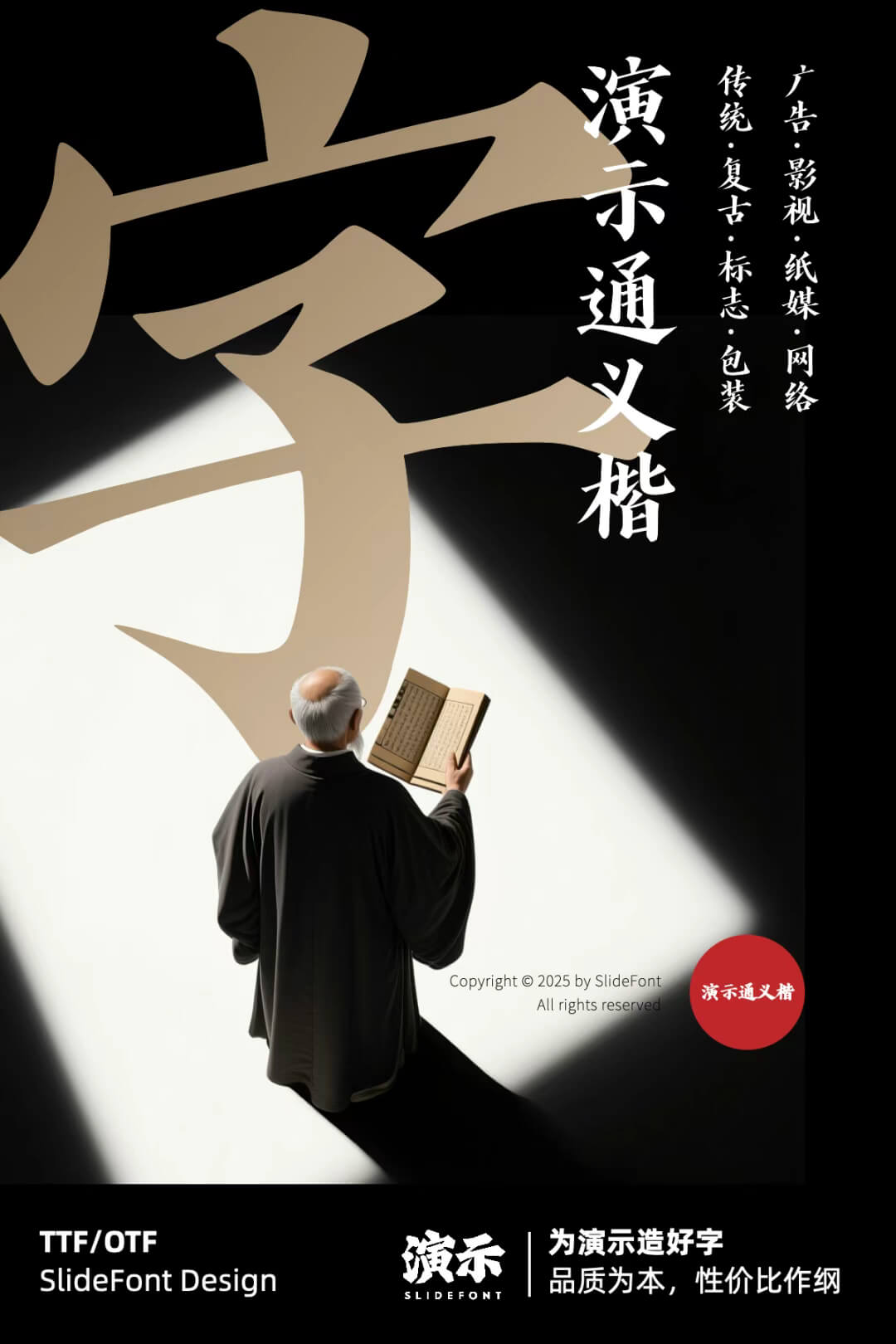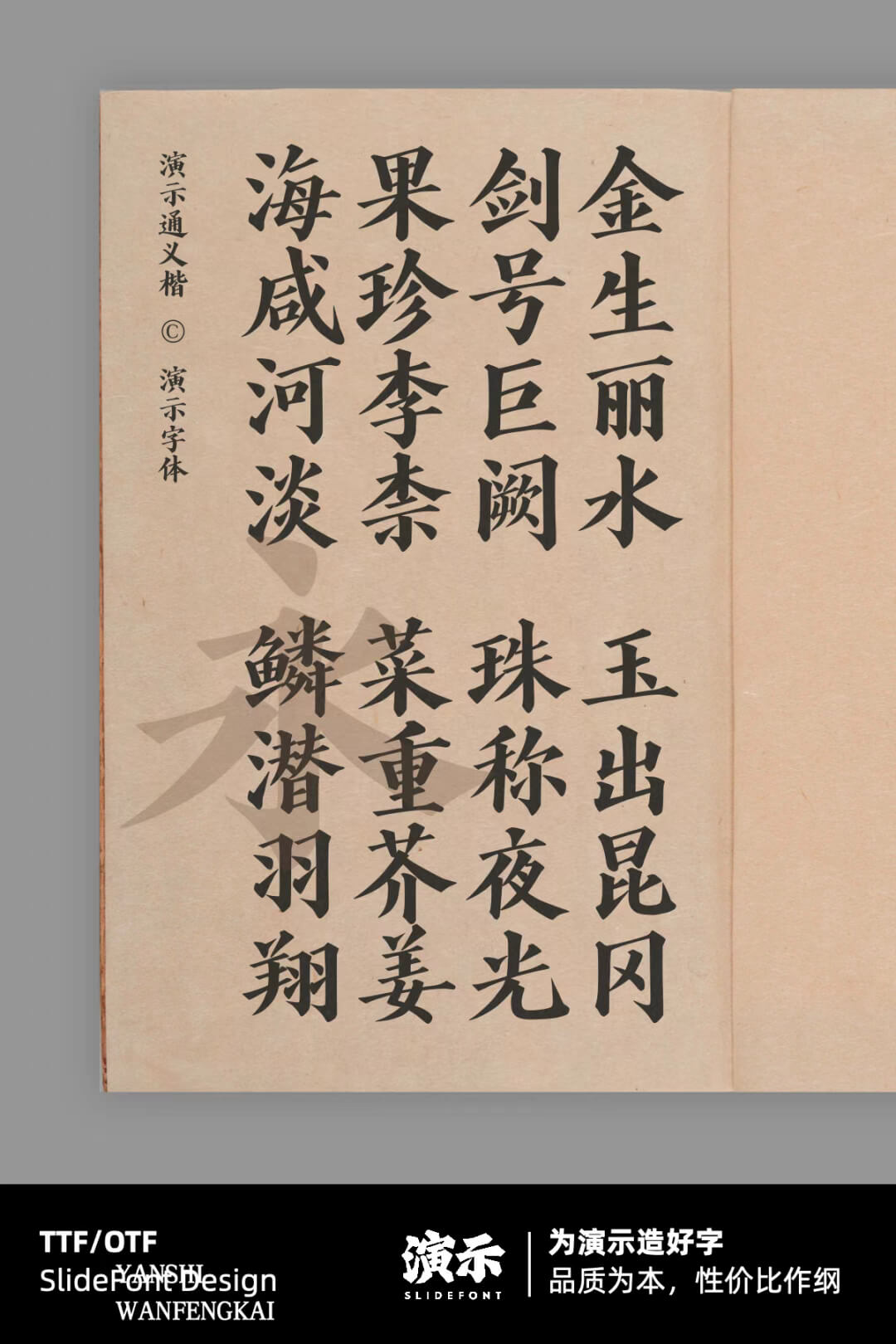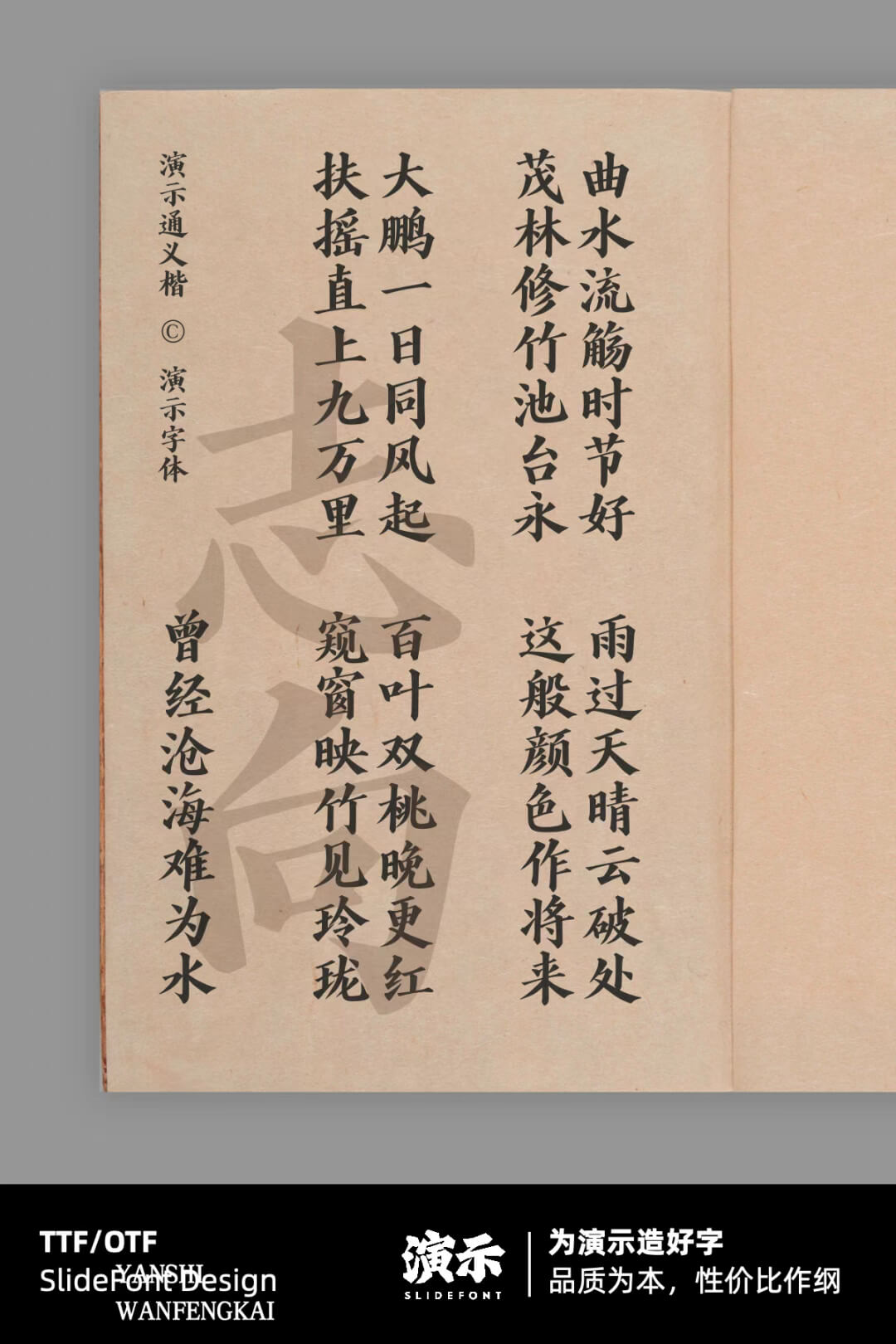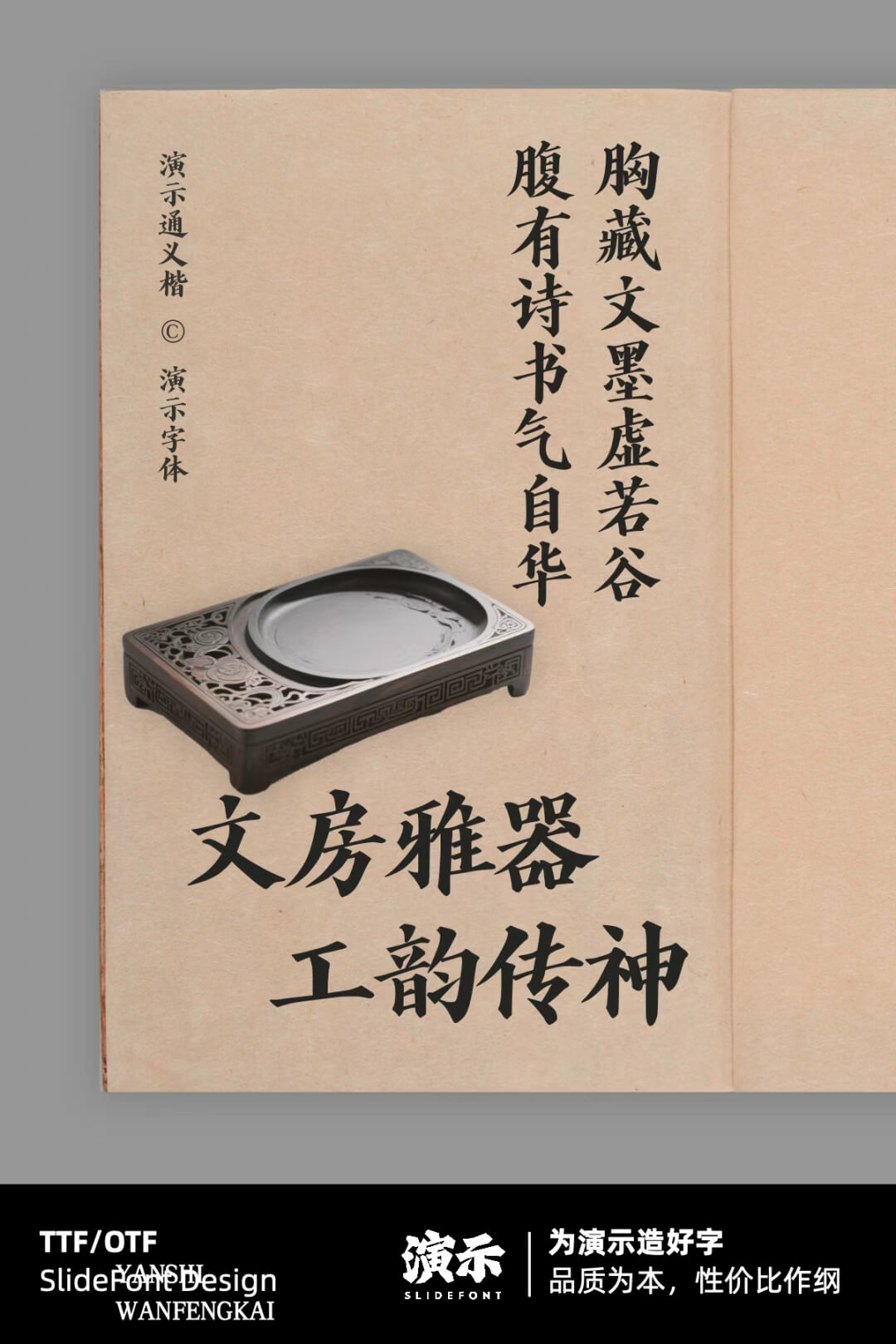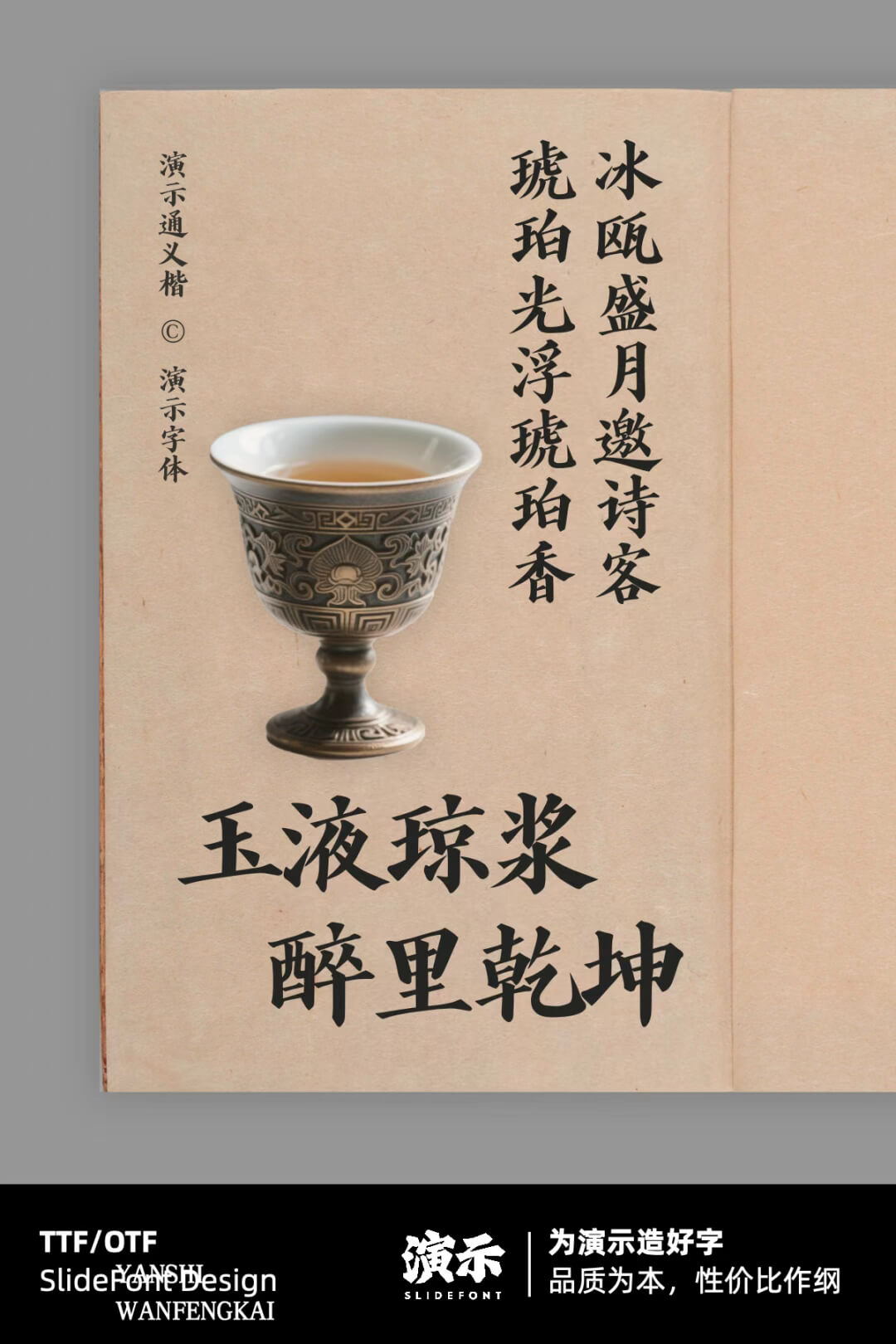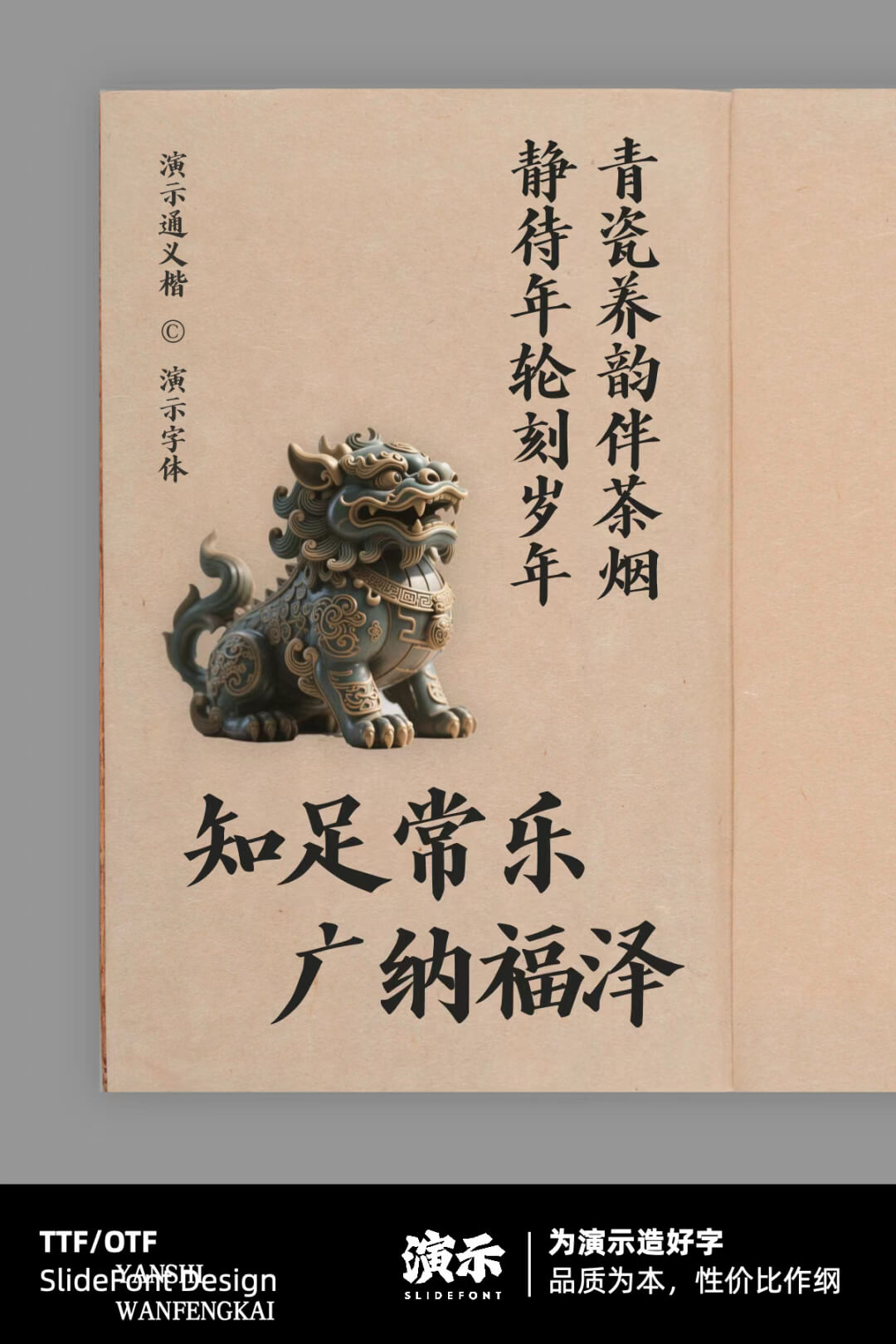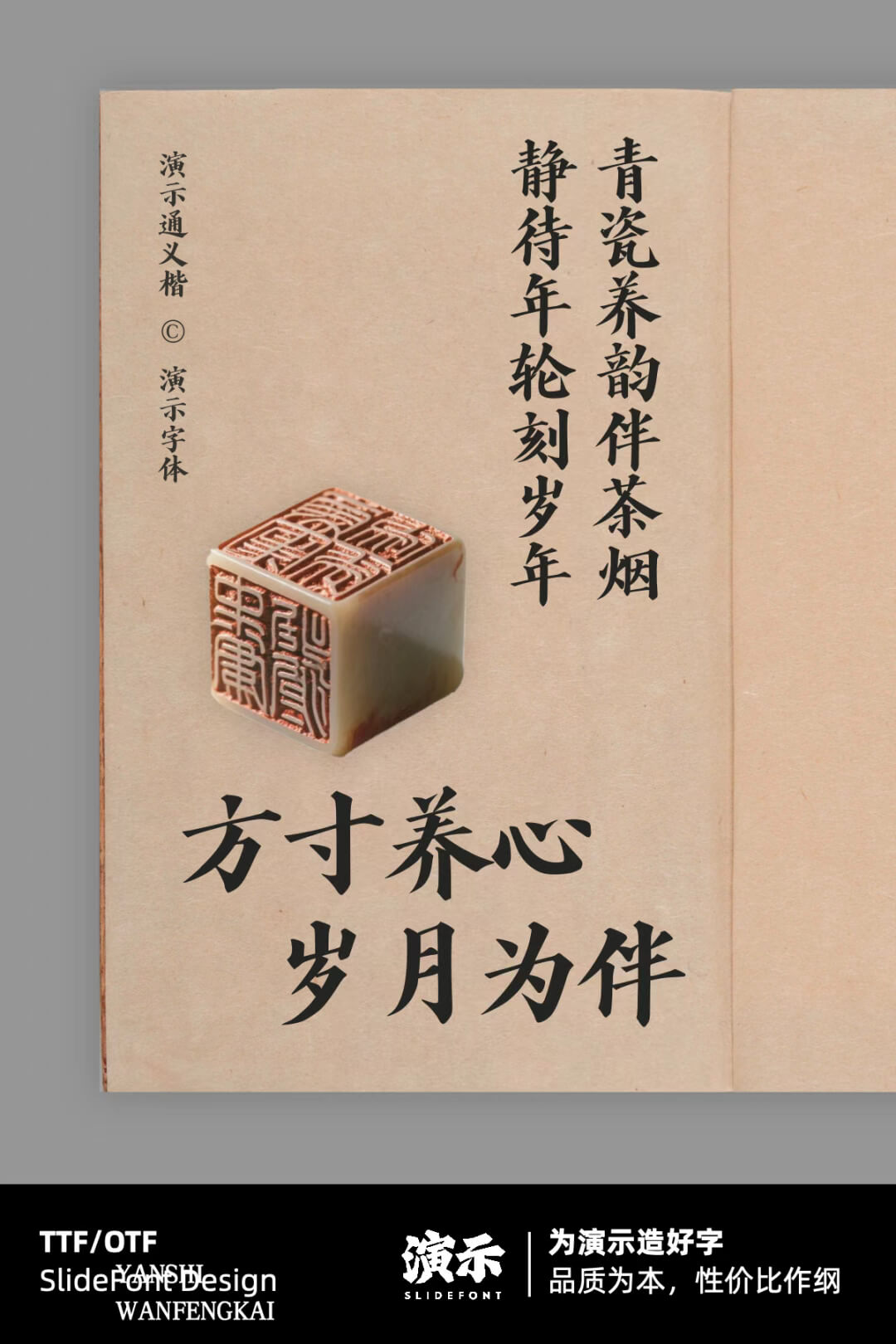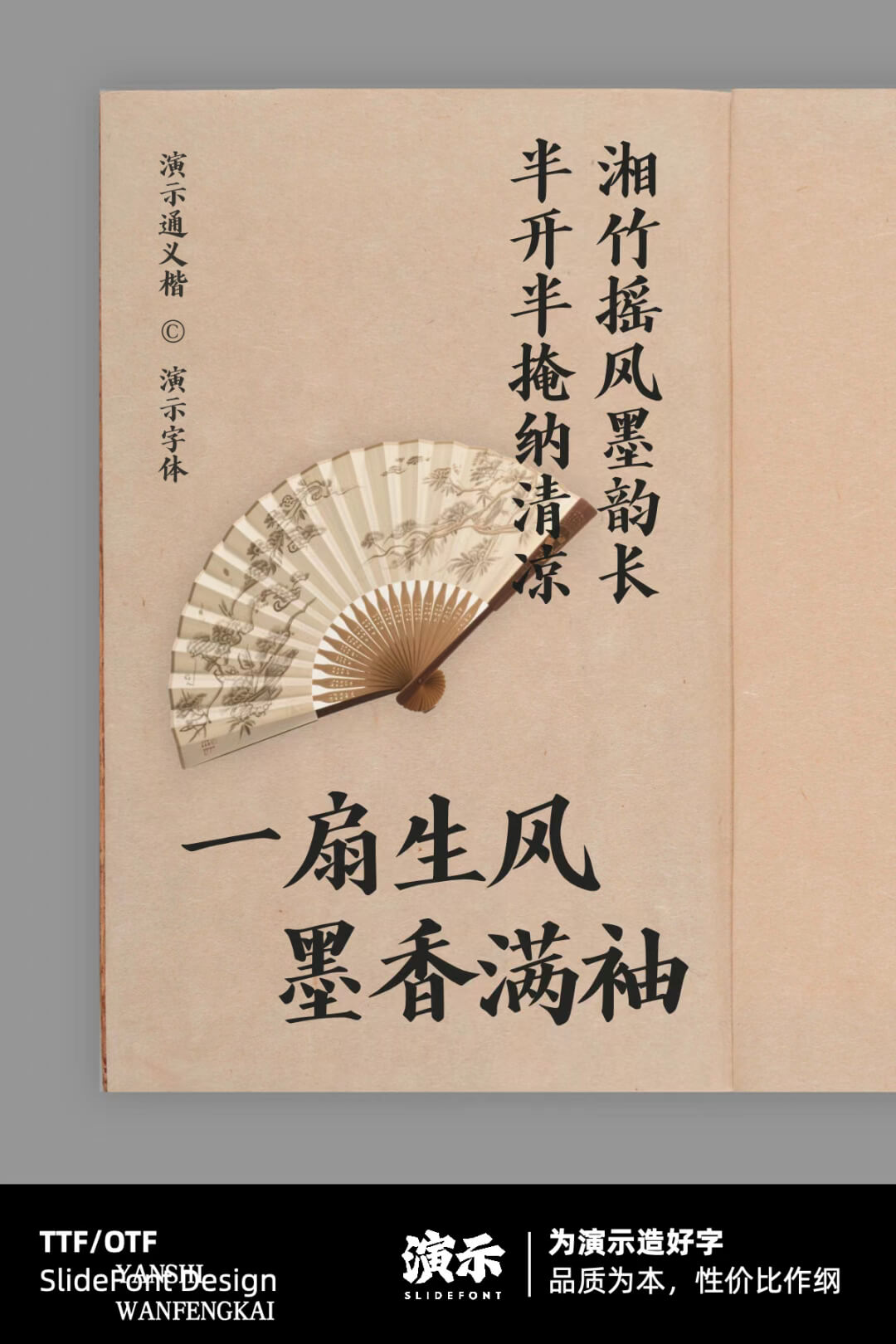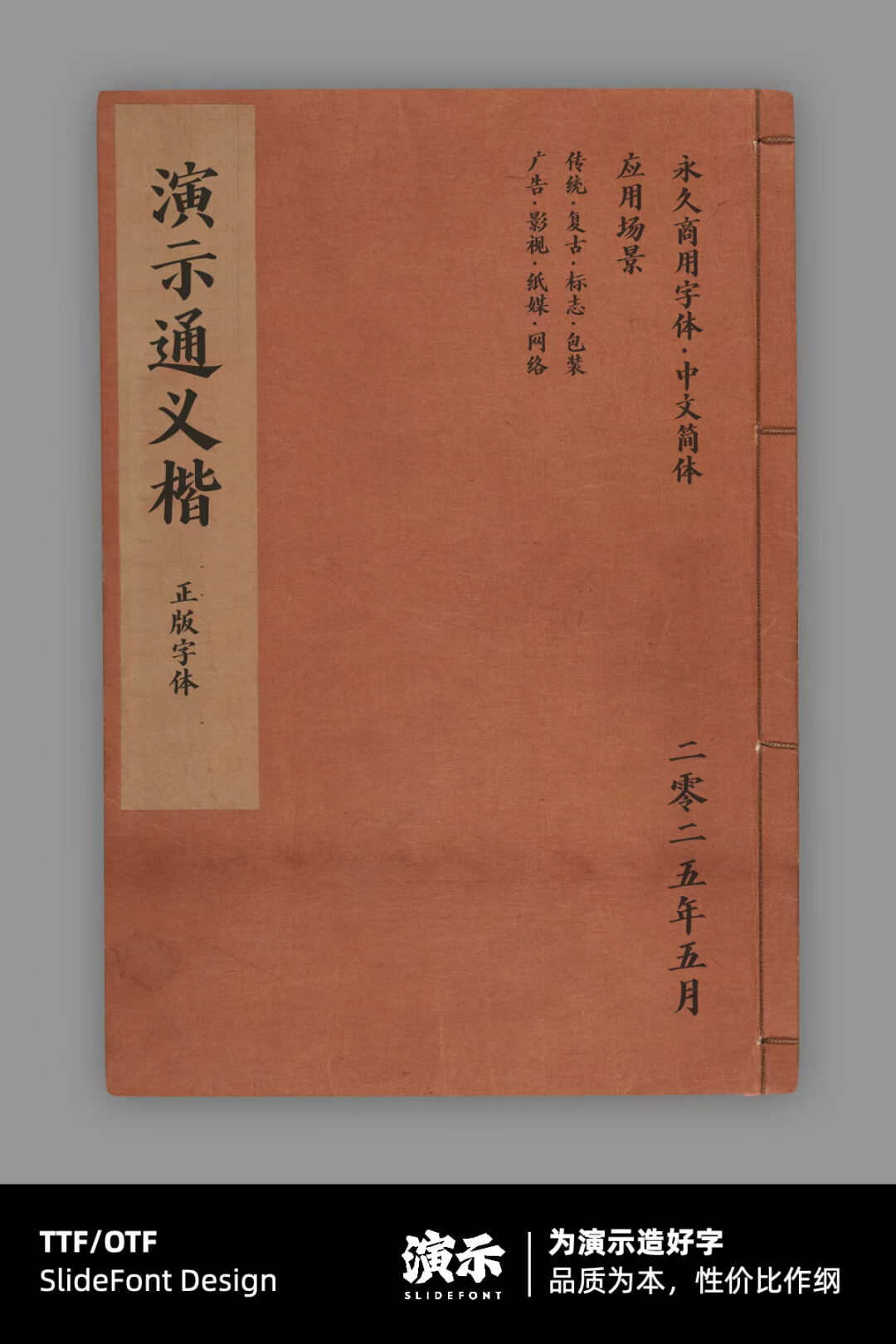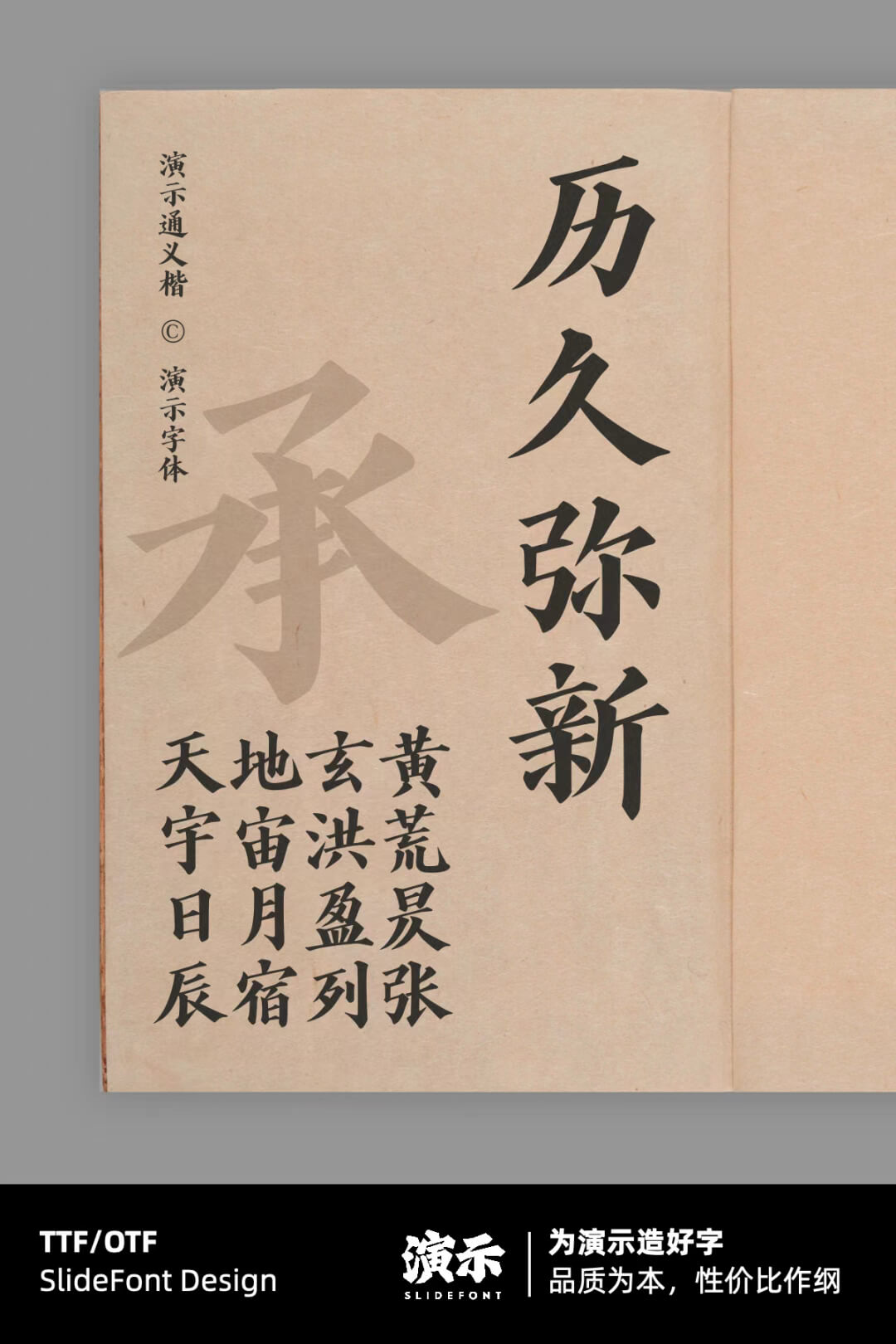
演示通义楷
演示通义楷是由演示字体推出的楷书刻本字体。灵感取自西汉司马迁撰南宋建安黄善夫家塾刊本,保留楷体规整、端庄的韵味,笔画粗细适中,转折自然流畅,尽显古朴典雅。在现代设计需求的驱动下,该字体通过优化细节,增强了文字的可读性与视觉吸引力。这种字体正式规范,适用于商务报告、学术文档的标题,彰显专业严谨;又富有亲和力,在文化宣传、教育资料中使用,能拉近与受众的距离。大字号使用时,其醒目的特性快速抓住读者目光,提升信息传达效率,增强版面层次感,让文档主题重点一目了然。